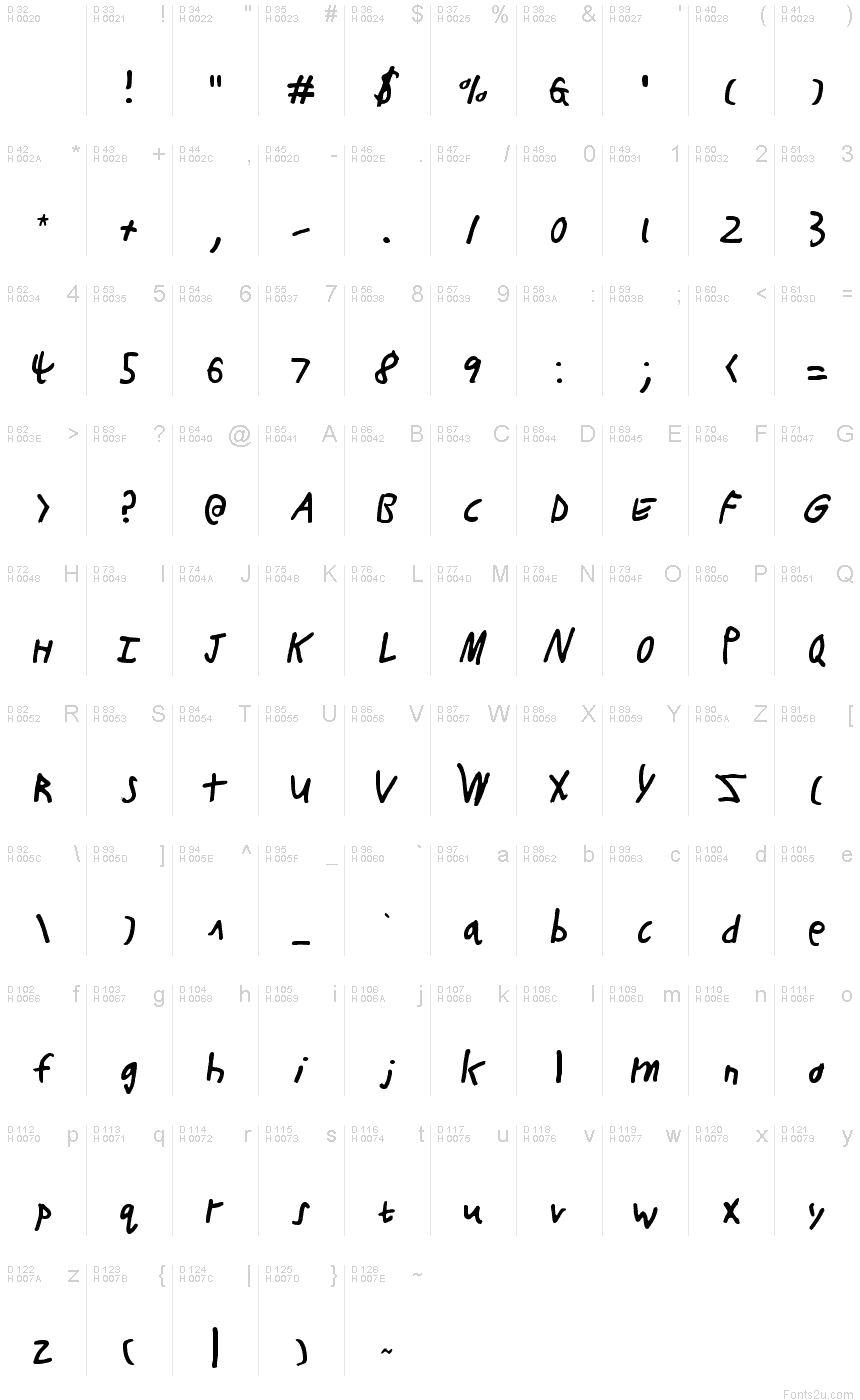
Buttons the Bear Light od Iconian Fonts to darmowy, wyrazisty krój pisma typu display, utrzymany w zabawnym, bajkowym klimacie. Szerokie pociągnięcia przypominające pędzel, miękkie łuki i nieregularne kształty liter nadają pismu lekkości i naturalnej dynamiki, nie czyniąc go przy tym zbyt skomplikowanym.
Świetnie sprawdzi się na okładkach książek dla dzieci, opakowaniach zabawek, plakatach edukacyjnych, zaproszeniach na przyjęcia oraz radosnych grafikach marki. Ten darmowy font szczególnie dobrze prezentuje się w krótkich nagłówkach i na kartach tytułowych, gdzie jego hojne kształty i nieregularny rytm potrafią nadać charakteru całemu projektowi.
Buttons the Bear Light